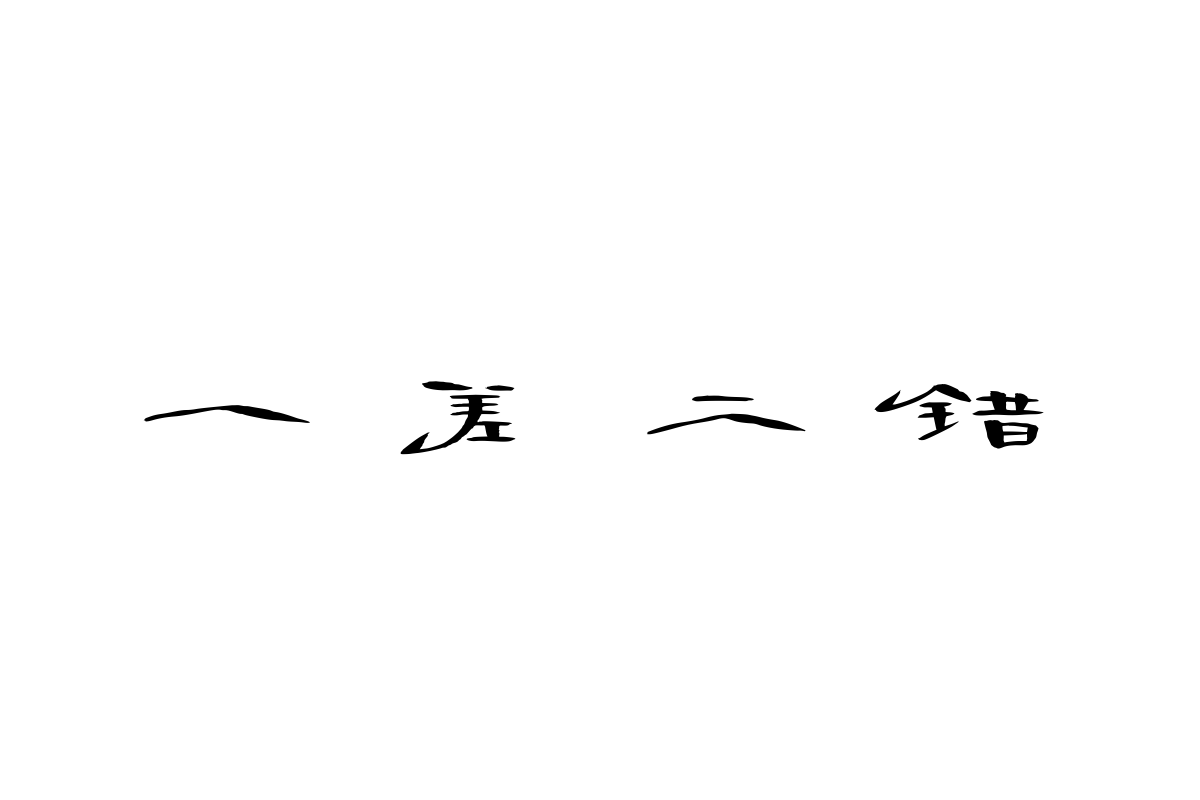
汉仪袁体隶书是一款由汉仪公司开发的字体,具有独特的书法风格和艺术感。这款字体采用了传统的隶书结构,笔画流畅,线条清晰,给人一种古朴典雅的感觉。同时,字体的大小、粗细、间距等都可以自由调整,方便用户根据需要制作出各种风格的设计作品。
汉仪袁体隶书的特点在于其笔画的粗细变化,使得字体既有力度又有柔美,既有传统韵味又有现代气息。这种独特的风格使得汉仪袁体隶书在众多字体中脱颖而出,受到了广大设计师的喜爱和认可。
总的来说,汉仪袁体隶书是一款非常优秀的字体,无论是用于印刷品还是网络设计,都能展现出其独特的魅力。